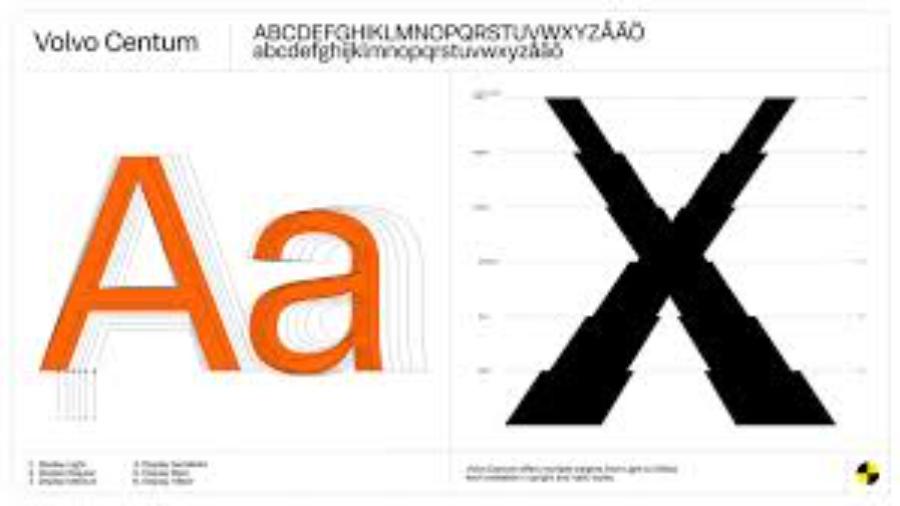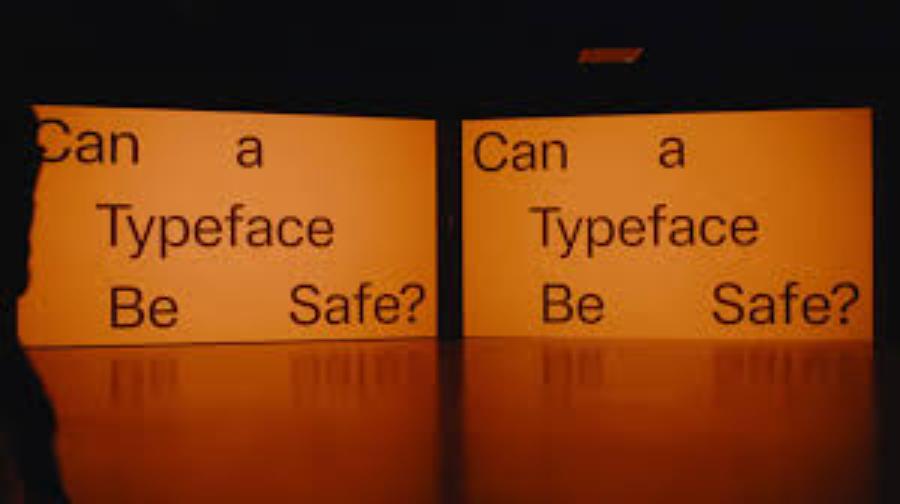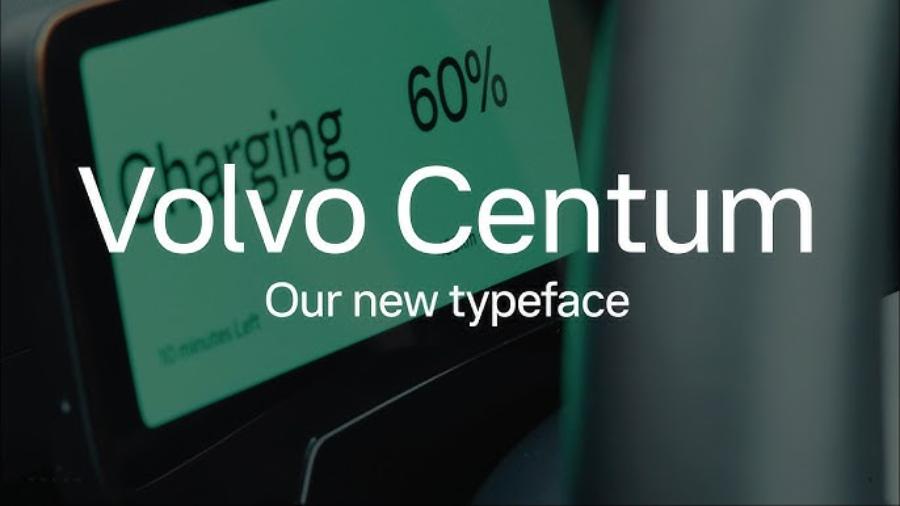
Volvo Ra Mắt Bộ Typeface Volvo Centum: Khi Kiểu Chữ Trở Thành Một Lớp An Toàn Mới Cho Kỷ Nguyên Số
Khám phá Volvo Centum - bộ typeface mới đột phá của Volvo giúp tối ưu hóa khả năng đọc và an toàn giao thông. Tìm hiểu cách kiểu chữ trở thành lớp bảo vệ mới trong thiết kế ô tô hiện đại.
Volvo Ra Mắt Bộ Typeface Volvo Centum: Khi Kiểu Chữ Trở Thành Một Lớp An Toàn Mới Cho Kỷ Nguyên Số
Sự ra đời của bộ chữ Volvo Centum đánh dấu một cột mốc quan trọng trong lịch sử thiết kế của hãng xe Thụy Điển, khẳng định triết lý lấy con người làm trung tâm đã được nâng tầm lên một tiêu chuẩn mới. Trong thế giới ô tô hiện đại, nơi các màn hình kỹ thuật số đang dần thay thế các nút bấm vật lý, khả năng tiếp nhận thông tin nhanh chóng và chính xác của người lái trở thành yếu tố sống còn. Volvo Centum không đơn thuần là một thay đổi về mặt thẩm mỹ đồ họa, mà là một giải pháp kỹ thuật được tính toán tỉ mỉ để giảm thiểu sự xao nhãng và tăng cường khả năng phản xạ. Việc triển khai bộ typeface riêng biệt này cho thấy tầm nhìn xa của Volvo trong việc biến những chi tiết nhỏ nhất thành một phần của hệ thống an toàn chủ động, giúp người lái duy trì sự tập trung tối đa vào cung đường phía trước.
1. Triết lý thiết kế Thụy Điển và sự ra đời của Volvo Centum
Ngôn ngữ thiết kế của Volvo luôn gắn liền với sự tối giản, công năng và sự tinh tế đặc trưng của vùng Scandinavia. Volvo Centum xuất hiện như một sự kế thừa hoàn hảo những giá trị đó, đồng thời đáp ứng các thách thức mới của kỷ nguyên xe điện và xe tự lái.
1.1 Sự chuyển dịch từ ngôn ngữ cũ sang tiêu chuẩn mới
Trước khi Volvo Centum ra đời, hãng xe này đã sử dụng nhiều kiểu chữ khác nhau cho các mục đích truyền thông và giao diện người dùng. Tuy nhiên, sự phân mảnh này đôi khi tạo ra những rào cản nhỏ trong việc nhận diện thương hiệu và sự đồng nhất về trải nghiệm thị giác. Việc tập hợp tất cả vào một bộ typeface duy nhất giúp Volvo tạo ra một tiếng nói đồng nhất, từ bảng điều khiển trên xe đến các ứng dụng di động và tài liệu in ấn. Cái tên "Centum" (nghĩa là một trăm trong tiếng Latin) cũng ám chỉ kỷ niệm 100 năm hình thành và phát triển của hãng, đánh dấu một thế kỷ đổi mới không ngừng.
1.2 Tầm quan trọng của Typography trong giao diện xe hơi hiện đại
Trong cabin của một chiếc xe thế hệ mới, người lái phải xử lý hàng loạt thông tin từ bản đồ, tình trạng pin, tốc độ đến các cảnh báo an toàn chỉ trong một cái liếc mắt. Một kiểu chữ không phù hợp có thể gây ra sự nhầm lẫn giữa các con số (như số 3, số 7 hoặc số 0) hoặc làm chậm quá trình đọc hiểu trong điều kiện ánh sáng yếu. Volvo Centum được tạo ra để giải quyết triệt để những vấn đề này, biến việc đọc thông tin trở nên tự nhiên và tốn ít năng lượng não bộ nhất có thể.
2. Các đặc điểm kỹ thuật giúp Volvo Centum tối ưu hóa sự an toàn
Mỗi đường nét, khoảng cách và độ dày của Volvo Centum đều được đội ngũ chuyên gia thiết kế đồ họa phối hợp với các kỹ sư an toàn để thử nghiệm trong nhiều điều kiện vận hành khắc nghiệt.
2.1 Độ mở của các chữ cái và khả năng nhận diện nhanh
Đặc điểm nổi bật nhất của Volvo Centum là độ mở (aperture) của các chữ cái như 'c', 'e', 's' rất rộng. Điều này giúp ngăn chặn hiện tượng các chữ cái bị nhòe vào nhau khi nhìn từ khoảng cách xa hoặc trong điều kiện rung lắc khi xe di chuyển. Đối với người lái, điều này có nghĩa là họ có thể nhận diện thông báo trên màn hình HUD (Head-up Display) nhanh hơn vài mili giây so với các phông chữ truyền thống. Trong các tình huống khẩn cấp, vài mili giây này chính là ranh giới giữa an toàn và nguy hiểm.
2.2 Sự cân bằng giữa tính thẩm mỹ và công năng hình học
Volvo Centum mang trong mình vẻ đẹp của sự hiện đại với các đường nét hình học sạch sẽ. Tuy nhiên, thay vì chạy theo xu hướng thiết kế phẳng quá mức làm mất đi tính đặc thù của ký tự, bộ chữ này duy trì những điểm nhấn riêng biệt để mắt người dễ dàng phân biệt giữa các chữ cái có hình dạng tương đồng. Sự cân bằng này giúp giao diện xe không chỉ đẹp mắt, sang trọng mà còn cực kỳ hiệu quả trong việc truyền tải thông điệp.
3. Ứng dụng của Volvo Centum trong hệ sinh thái trải nghiệm người dùng
Bộ typeface mới không chỉ nằm lại ở các màn hình giải trí mà len lỏi vào từng chi tiết nhỏ nhất trong trải nghiệm sở hữu xe Volvo.
3.1 Tối ưu hóa màn hình lái kỹ thuật số và hệ thống Infotainment
Trên các dòng xe điện như EX30 hay EX90, Volvo Centum đóng vai trò chủ đạo trong việc hiển thị các thông số vận hành. Độ tương phản của kiểu chữ này trên nền màn hình đen sâu giúp các con số trở nên sắc nét, giảm thiểu tình trạng mỏi mắt cho người lái khi di chuyển vào ban đêm. Việc đồng bộ hóa phông chữ giữa màn hình trung tâm và cụm đồng hồ phía sau tay lái tạo ra một dòng chảy thông tin liền mạch, giúp người dùng cảm thấy thư thái và tự tin hơn.
3.2 Nhất quán trên các nền tảng truyền thông và ứng dụng di động
Khách hàng của Volvo sẽ bắt gặp Volvo Centum từ khi tìm hiểu xe trên trang web, đọc Catalogue đến khi sử dụng ứng dụng Volvo Cars để điều khiển xe từ xa. Sự nhất quán này củng cố niềm tin vào sự tỉ mỉ của thương hiệu. Khi một hãng xe đầu tư công sức vào một bộ chữ, họ đang gửi đi thông điệp rằng họ quan tâm đến mọi chi tiết nhỏ nhất trong cuộc sống của khách hàng.
4. Volvo Centum và triết lý "Lớp an toàn mới" trong thiết kế
Khái niệm "kiểu chữ là lớp an toàn" nghe có vẻ trừu tượng nhưng lại mang tính thực tiễn cao khi phân tích dưới góc độ tâm lý học nhận thức và công thái học.